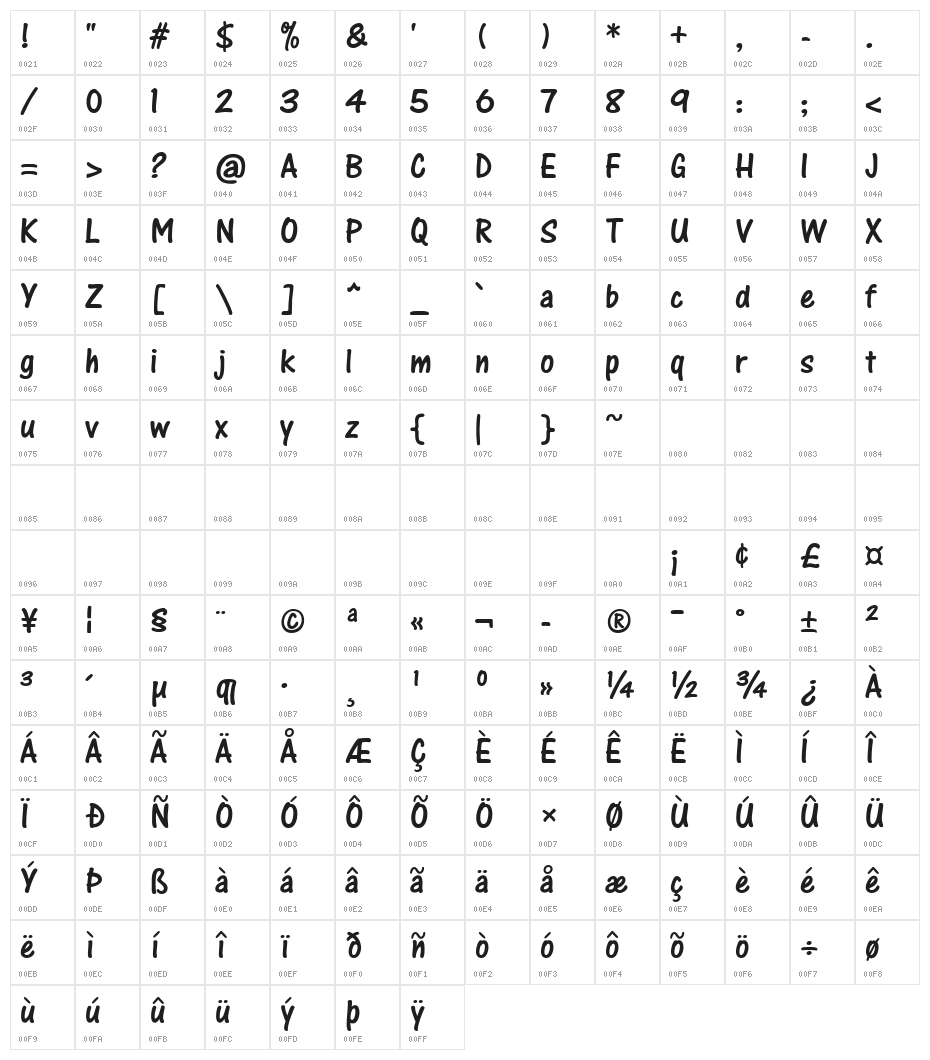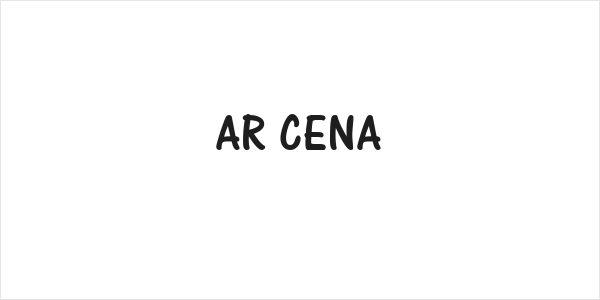
AR CENA Font
| النمط العام | Casual |
| حالة الاستخدام | Headlines, Logos, Informal Text |
| مشاريع مقترحة | Ideal for invitations, greeting cards, playful branding, and informal designs. |